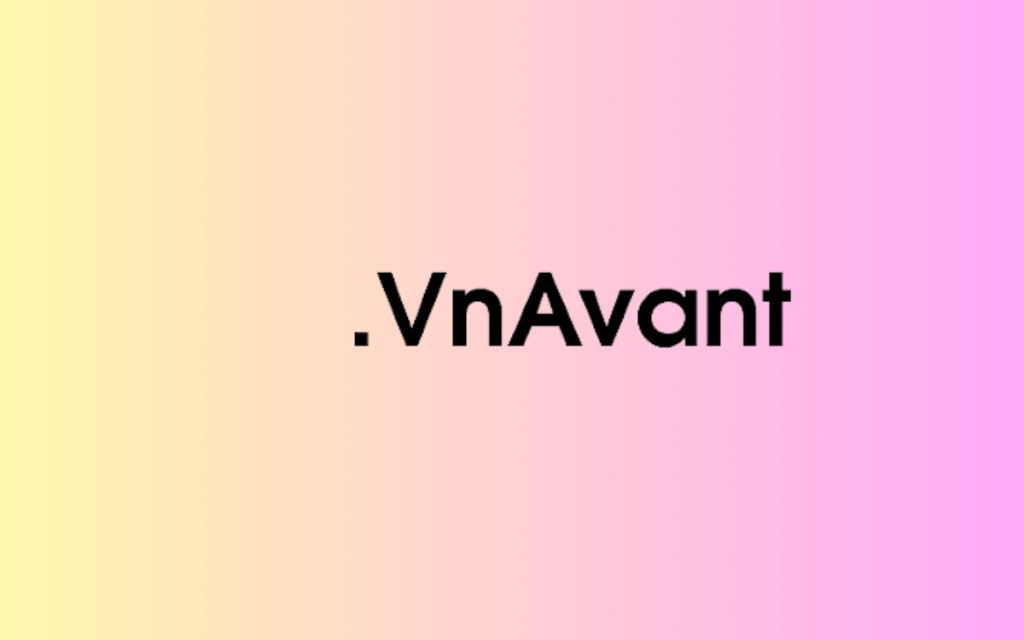
Font Chữ Vnavant
Độ dày: Regular, Bold
Font chữ Vnavant là một lựa chọn phổ biến trong thiết kế đồ họa và in ấn tại Việt Nam, đặc biệt phù hợp cho các văn bản cần sự hiện đại và tinh tế. Với các đường nét rõ ràng, gọn gàng và thuộc bộ font chữ không chân (sans-serif), Font Chữ Vnavant giúp văn bản trở nên dễ đọc và bắt mắt hơn. Font chữ này thường được sử dụng trong các dự án thiết kế liên quan đến quảng cáo, thương hiệu, và các tài liệu chuyên nghiệp nhờ vào tính thẩm mỹ cao và sự linh hoạt trong cách trình bày. Sự kết hợp giữa phong cách hiện đại và khả năng tương thích tốt với tiếng Việt khiến Font Chữ Vnavant trở thành một công cụ đắc lực trong tay các nhà thiết kế.